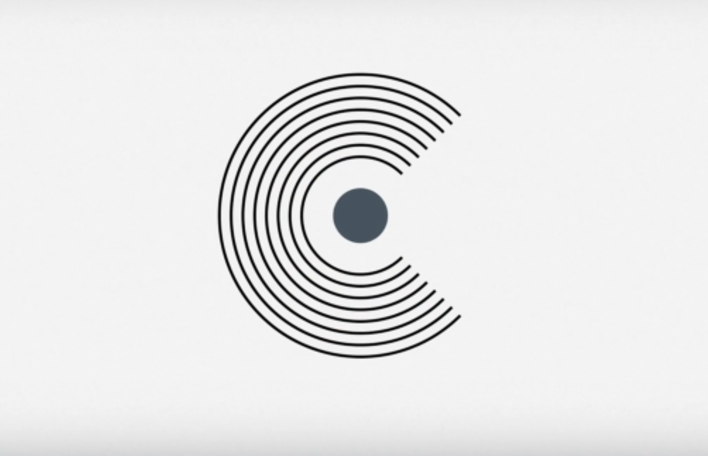
Une superbe animation typographique initiée par le studio Calango, basé à Amsterdam. Un travail très sobre et efficace d’une durée de 1min10 et intitulé « Moshun ». Le tout sur une bande son réalisée par Datasette. A découvrir en images et en vidéo dans la suite de l’article.